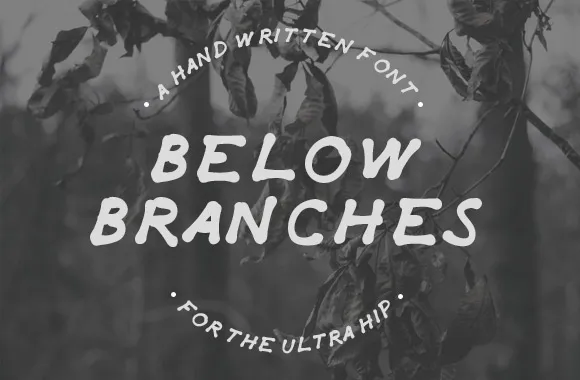
A Below Branches Font é uma escolha perfeita para quem procura algo autêntico e antigo em seu trabalho visual. Inspirada no estilo vintage, esta fonte foi cuidadosamente desenhada para manter um aspecto de escrita a mão, tornando-a legível mesmo nas menores proporções. O seu propósito é destacar trabalhos ilustrativos de forma única e sofisticada. Ideal tanto para o design gráfico quanto para o layout editorial, esta fonte oferece uma opção versátil que combina clareza com um toque autoral. A Hamilton é a criador desta fonte elegante que não apenas brilha nas grandes apostas de design, mas também nas oportunidades mais sutis e delicadas. Eles são perfeitos para aqueles que buscam uma linguagem única na escrita de suas ideias visuais.